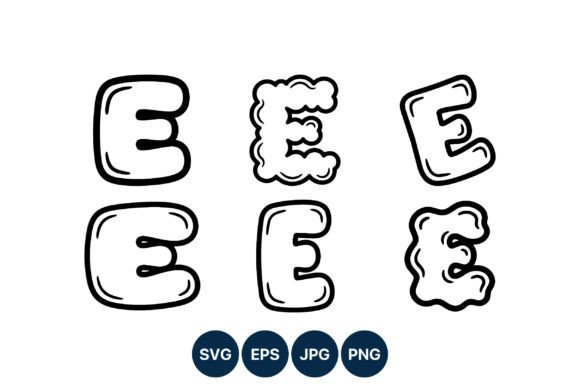
Bubble Letter E Playful Font Set
Jika anda sedang mencari aset berkualiti tinggi seperti Bubble Letter E Playful Font Set, pakej premium ini merupakan pilihan yang hebat untuk projek kreatif anda.
Dicipta dengan ketepatan, Bubble Letter E Playful Font Set menyediakan vektor yang bersih, tipografi yang licin dan lesen komersial untuk ketenangan fikiran.
Sama ada anda mencipta produk POD (Print on Demand), jemputan perkahwinan atau grafik media sosial, Bubble Letter E Playful Font Set amat bersesuaian.